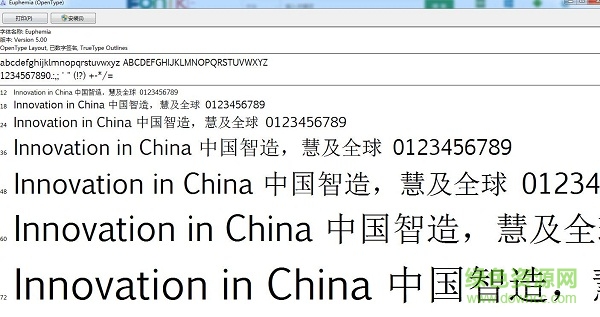
euphemiacas字體是一款規(guī)規(guī)矩矩的無襯線字體,結(jié)構(gòu)嚴謹,線條干脆不拖沓,適合用于平面設(shè)計、廣告牌、電子屏幕顯示、網(wǎng)頁設(shè)計等各大領(lǐng)域,喜歡的朋友快來下載吧!
無襯線字體往往被用在標題、較短的文字段落或者一些通俗讀物中。相比嚴肅正經(jīng)的襯線體,無襯線體給人一種休閑輕松的感覺。